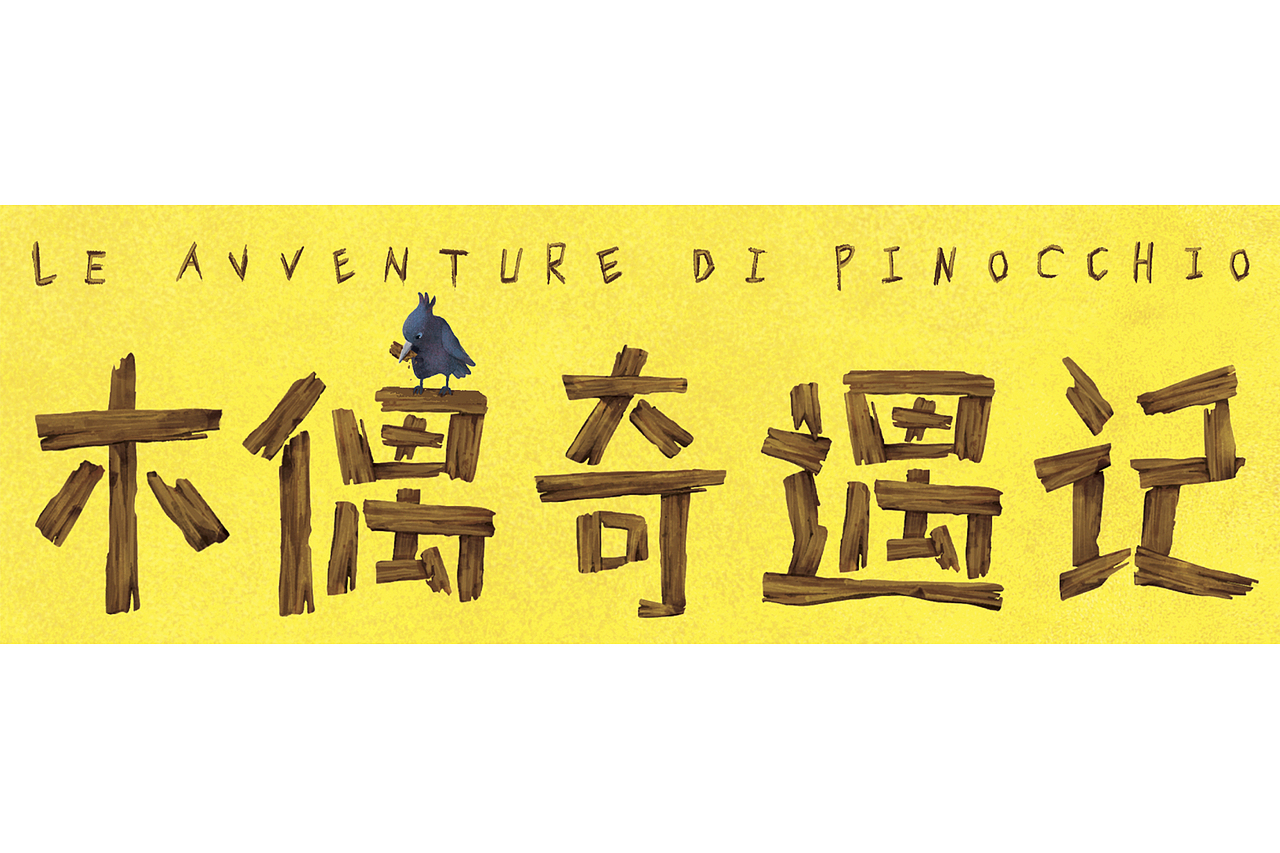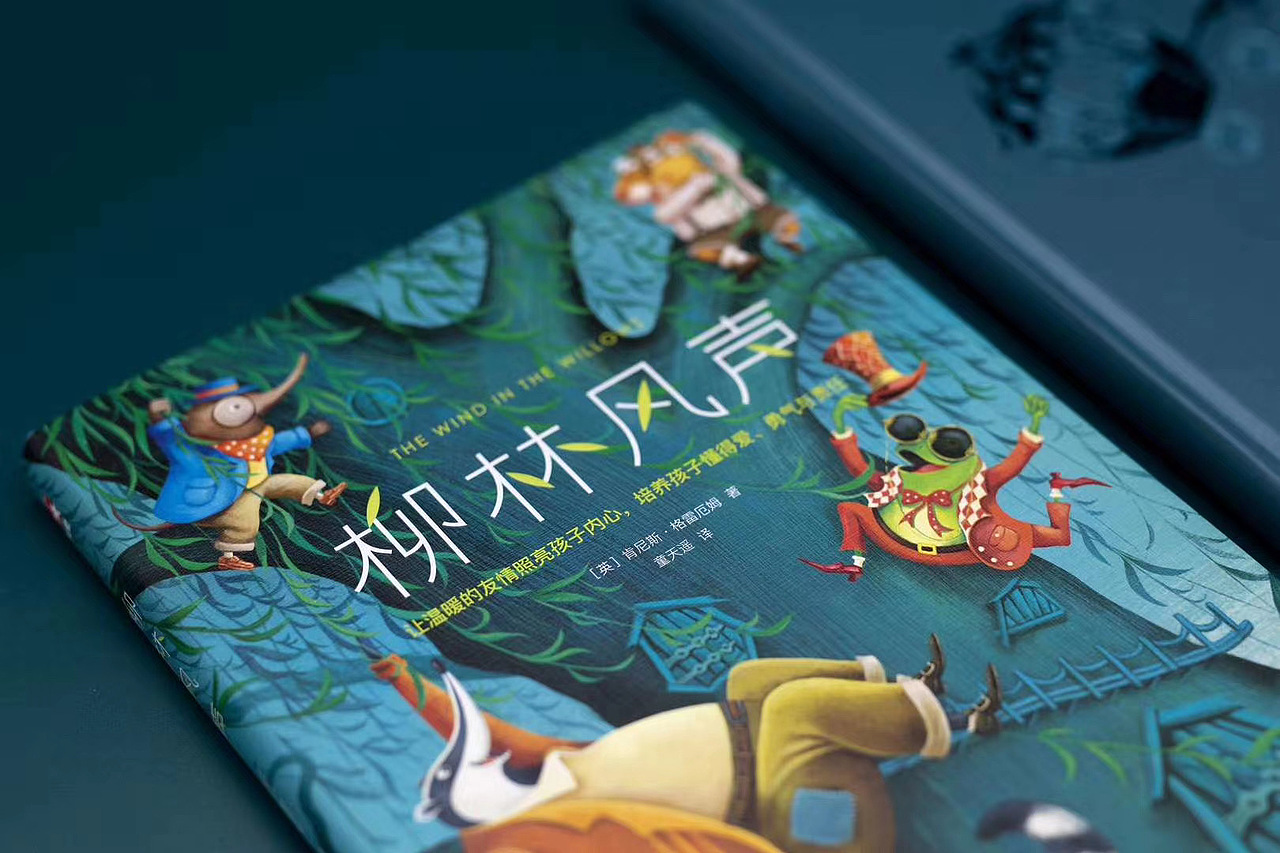
一、《列那狐的故事》
1、简介:《列那狐的故事》是由法国让娜·勒鲁瓦-阿莱改编的童话。该作讲述的是代表新兴市民阶级的列那狐在面对狮王的强权、公狼的霸道、雄鸡的弱小无助时,总能以自己的聪明机警左右逢源。它一方面欺压平民百姓,一方面同强权豪门勾心斗角,乃至战胜强大的对手。<br>2、图书定位:童书,7~16岁适度
一、《列那狐的故事》
1、简介:《列那狐的故事》是由法国让娜·勒鲁瓦-阿莱改编的童话。该作讲述的是代表新兴市民阶级的列那狐在面对狮王的强权、公狼的霸道、雄鸡的弱小无助时,总能以自己的聪明机警左右逢源。它一方面欺压平民百姓,一方面同强权豪门勾心斗角,乃至战胜强大的对手。
2、图书定位:童书,7~16岁适度
3、竞品分析:这些是市面上已经出过的版本
4、封面构思:列那狐是本书的主要角色,所以想以列那狐的形象为封面主要符号,用拟人的手法,表达出它幽默、狡猾的性格,更能符合本书的内容。此步骤需考虑文案、书名的摆放位置。
5、起手势:根据草图找狐狸、符合书中背景的服饰,符合列那狐男爵身份的发型
6、绘制封面
7、字体:结合列那狐狡黠的形象,和卷发相结合
8、摆好封面文案信息
9、内封:用了狐狸的橘色调,与封面先呼应,采用烫金工艺增加品质感。
10、贴纸设计:这本书的内插都是我绘制的,贴纸直接延用了内插的元素。
11、书签设计:用了大尾巴的符号,加深列那狐的形象
二、《柳林风声》
1、简介:《柳林风声》是以动物为主角的童话,文笔典雅,描写细致,富含哲理。书中塑造了几个可爱的动物形象:胆小怕事但又生性喜欢冒险的鼹鼠,热情好客、充满浪漫情趣的水鼠,侠义十足、具有领袖风范的老獾,喜欢吹牛、炫耀、追求时髦的蛤蟆,敦厚老实的水獭——他们生活在河岸或大森林里,有乐同享,有难同当。<br>2、图书定位:童书,7~16岁适度<br>
二、《柳林风声》
1、简介:《柳林风声》是以动物为主角的童话,文笔典雅,描写细致,富含哲理。书中塑造了几个可爱的动物形象:胆小怕事但又生性喜欢冒险的鼹鼠,热情好客、充满浪漫情趣的水鼠,侠义十足、具有领袖风范的老獾,喜欢吹牛、炫耀、追求时髦的蛤蟆,敦厚老实的水獭——他们生活在河岸或大森林里,有乐同享,有难同当。
2、图书定位:童书,7~16岁适度
3、竞品分析:市面上已出版的版本
4、封面构思:已出版过的版本大多以河、划船为场景;所以为另辟蹊径选用了柳树为主要符号和书名呼应,加上本书的4个性格鲜明的角色,他们的服装也是根据自己的性格特点去设计;比如蟾蜍的性格是非常外放,喜欢时髦,所以服装和造型也会比较浮夸,鲜艳.....
5、起手势:分别找了角色、柳树等参考
6、绘制封面
7、字体设计:因为封面图已经很丰富了,所以字体上不要太过花哨复杂,结合柳叶元素进行设计
8、摆放好封面文案信息
9、内封设计:烫金工艺,图案是4个角色骑着马车欢乐的样子
11、贴纸设计:这本书的内插都是我绘制的,贴纸直接延用了内插的元素。
12、书签设计:因为这几个角色的性格不同又十分鲜明,所以书签设计成异形的样式增加趣味感。
三、《十万个为什么》
1、简介:《十万个为什么》是已故苏联著名科普作家米·伊林于1929年出版的一套青少年科普书,是新中国几代青少年的科学启蒙读物。<br>2、图书定位:童书,科普,7~16岁适度<br>
三、《十万个为什么》
1、简介:《十万个为什么》是已故苏联著名科普作家米·伊林于1929年出版的一套青少年科普书,是新中国几代青少年的科学启蒙读物。
2、图书定位:童书,科普,7~16岁适度
3、竞品分析:版本对比
4、封面构思:这是本科普书,我想通过孩子在阅读探索中,发现许多乐趣。书里涌现出许多奇思妙想的元素,让孩子感受到阅读这本书是件特别有意思的事。
5、起手势:找了一些阅读场景的参考
6、绘制封面
7、摆放好封面文案信息
8、内封设计:用了蓝色和封面色调搭配,烫金工艺
10、书签设计
四、《草原上的小木屋》
1、简介:《草原上的小木屋》是美国经典名著《小木屋》系列小说中最有名最具代表性的作品。它的作者是罗兰·英格斯·怀德。罗兰根据自己的成长经历,费了十年的心血完成了《小木屋》系列小说。这套书记录了在美国西部拓荒热潮中,罗兰从两岁开始,就跟着爸爸妈妈四处迁移,艰苦开拓;直至拥有幸福生活的人生经历。<br>2、图书定位:童书,7~16岁适度<br>
四、《草原上的小木屋》
1、简介:《草原上的小木屋》是美国经典名著《小木屋》系列小说中最有名最具代表性的作品。它的作者是罗兰·英格斯·怀德。罗兰根据自己的成长经历,费了十年的心血完成了《小木屋》系列小说。这套书记录了在美国西部拓荒热潮中,罗兰从两岁开始,就跟着爸爸妈妈四处迁移,艰苦开拓;直至拥有幸福生活的人生经历。
2、图书定位:童书,7~16岁适度
3、竞品分析:市面上已出过的版本
4、封面构思:以小木屋为主要符号,这本书比较温暖,所以封面上想体现出一家人生活在草原上的欢乐景象。
5、起手势:分别找了草原参考,因为是全彩书,内插和封面的人物形象、元素最好要保持统一,所以封面直接延用了内插的元素。
6、封面绘制:书中描写的草原是黄色的,所以做了一些主观处理,黄色草原在网站上也能和别的版本进行区分,可以跳脱出来,有记忆点。
7、字体设计:笔划和木头元素相结合,“屋”字做了一些设计,书名中有一个突出的设计点就够了,否则会太多余显得花哨。
8、摆放好封面文案信息
9、条形码上做了一些设计,结合草原上的牛元素,增加趣味性。
10、内封设计:一家人其乐融融的图案,烫金工艺
11、藏书票设计
12、贴纸设计:延用了内插元素,内插插画师@乌克兰Sophia
四、《巴斯克维尔的猎犬》
1、简介:《巴斯克维尔的猎犬》是阿瑟·柯南·道尔的第三篇福尔摩斯系列小说,融合了侦探和哥特两种通俗的文类,并运用了双线叙述的手法。主要讲述了一只超自然的猎犬让夏洛克·福尔摩斯和华生医生来到了英格兰的乡村,调查查尔斯·巴斯克维尔爵士被杀的原因的故事。<br>2、图书定位:童书,悬疑,7~16岁适度<br>
四、《巴斯克维尔的猎犬》
1、简介:《巴斯克维尔的猎犬》是阿瑟·柯南·道尔的第三篇福尔摩斯系列小说,融合了侦探和哥特两种通俗的文类,并运用了双线叙述的手法。主要讲述了一只超自然的猎犬让夏洛克·福尔摩斯和华生医生来到了英格兰的乡村,调查查尔斯·巴斯克维尔爵士被杀的原因的故事。
2、图书定位:童书,悬疑,7~16岁适度
这是之前同事圈圈画的草图,离职后这个项目由我接手,继续推进下去。
3、竞品分析:版本对比
4、起手势:针对之前的版本我找了一些参考继续深入下去,一是加深猎犬的特征,二是突出猎犬眼珠和眼珠下的人这一视觉焦点,三是牙齿和城堡的设计结合的更加明显,四是细节优化
5、色调参考:这是一部悬疑风格的书,所以色调上不太适合前面那种欢快亮丽的颜色,应该是偏悬疑,有氛围感,色调上偏冷的处理。
画着画着,想把画面延伸到左右勒口,更加有气势感
6、《巴斯克维尔的猎犬》是福尔摩斯探案故事的代表作,所以封面上设计了福尔摩斯的logo,增加阅读人群。
7、摆放好封面文案信息
五、《木偶奇遇记》
1、简介:《木偶奇遇记》是一部由意大利作家卡洛·科洛迪创作的童话,也是其代表作,于1880年首次出版。作品主要讲述了木偶匹诺曹在被赋予生命后经历了一系列冒险,变得诚实、勤劳、善良,成为了一个真真正正的男孩。《木偶奇遇记》被认为是儿童古典文学经典之一,曾多次被翻拍成电影。<br>2、图书定位:童书,7~16岁适度<br>
五、《木偶奇遇记》
1、简介:《木偶奇遇记》是一部由意大利作家卡洛·科洛迪创作的童话,也是其代表作,于1880年首次出版。作品主要讲述了木偶匹诺曹在被赋予生命后经历了一系列冒险,变得诚实、勤劳、善良,成为了一个真真正正的男孩。《木偶奇遇记》被认为是儿童古典文学经典之一,曾多次被翻拍成电影。
2、图书定位:童书,7~16岁适度
3、竞品分析:版本对比
这本书原先是外签俄罗斯插画师Lera House绘制,但是交稿后觉得还是有很多地方可以继续优化下去,于是也找了一些参考继续优化下去
4、起手势:我找了一些优秀的插画作为参考,在细节和颜色的运用上有很大的帮助
调整前后对比,之前的画比较扁平缺少细节,颜色上也比较单一
5、字体设计:我结合了木头的元素,和书名相呼应,在“偶”字上和乌鸦进行了互动。
6、细化完成
7、摆放好封面文案信息
8、内封设计:选了一款和木头形式的纸张材质,烫金工艺。